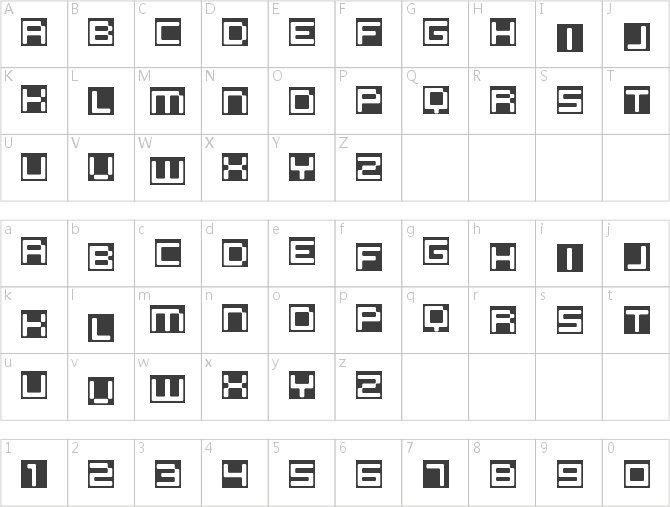
BIG_GIPSY_BRO 詳情頁
字體名稱: BIG_GIP
BIG_GIPSY_BRO
BIG_GIPSY_BRO介紹
BIG_GIPSY_BRO字體字庫是一款讓人賞心悅目、百看不厭的英文字體,適合各類廣告和產(chǎn)品包裝設(shè)計(jì)應(yīng)用,字體大小0.09MB,格式為ttf字體,上傳用戶是得·岸,作者/版權(quán)方為未知